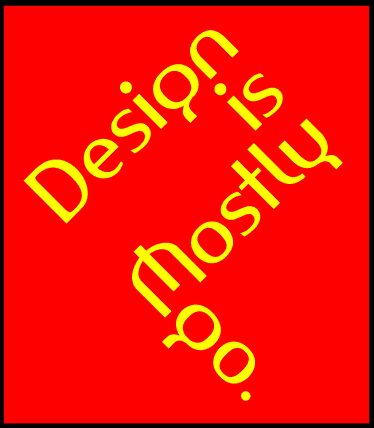
Amerika Sans
Amerika Sans od Apostrophic Labs to darmowy krój bezszeryfowy z nutą luźnego, odręcznego stylu. Płynne, monolinearne pociągnięcia i zaokrąglone krzywizny nadają słowom delikatny rytm, przywodzący na myśl pismo wykonane cienkim markerem. Zaokrąglone zakończenia i otwarte światła sprawiają, że font jest czysty i lekki, dzięki czemu nawet w większym rozmiarze zachowuje przyjazny charakter bez wrażenia przytłoczenia.
Amerika Sans to nowoczesny, niezobowiązujący wybór, który świetnie sprawdzi się na plakatach, w brandingu kawiarni czy studiów, grafikach do mediów społecznościowych, opakowaniach, logo oraz w zabawnym UI. Ten darmowy font wygląda znakomicie przy nieco większym światle między literami w nagłówkach; zestaw go z neutralnym geometrycznym bezszeryfem w tekście głównym, aby zachować równowagę i wyrazistość projektu.